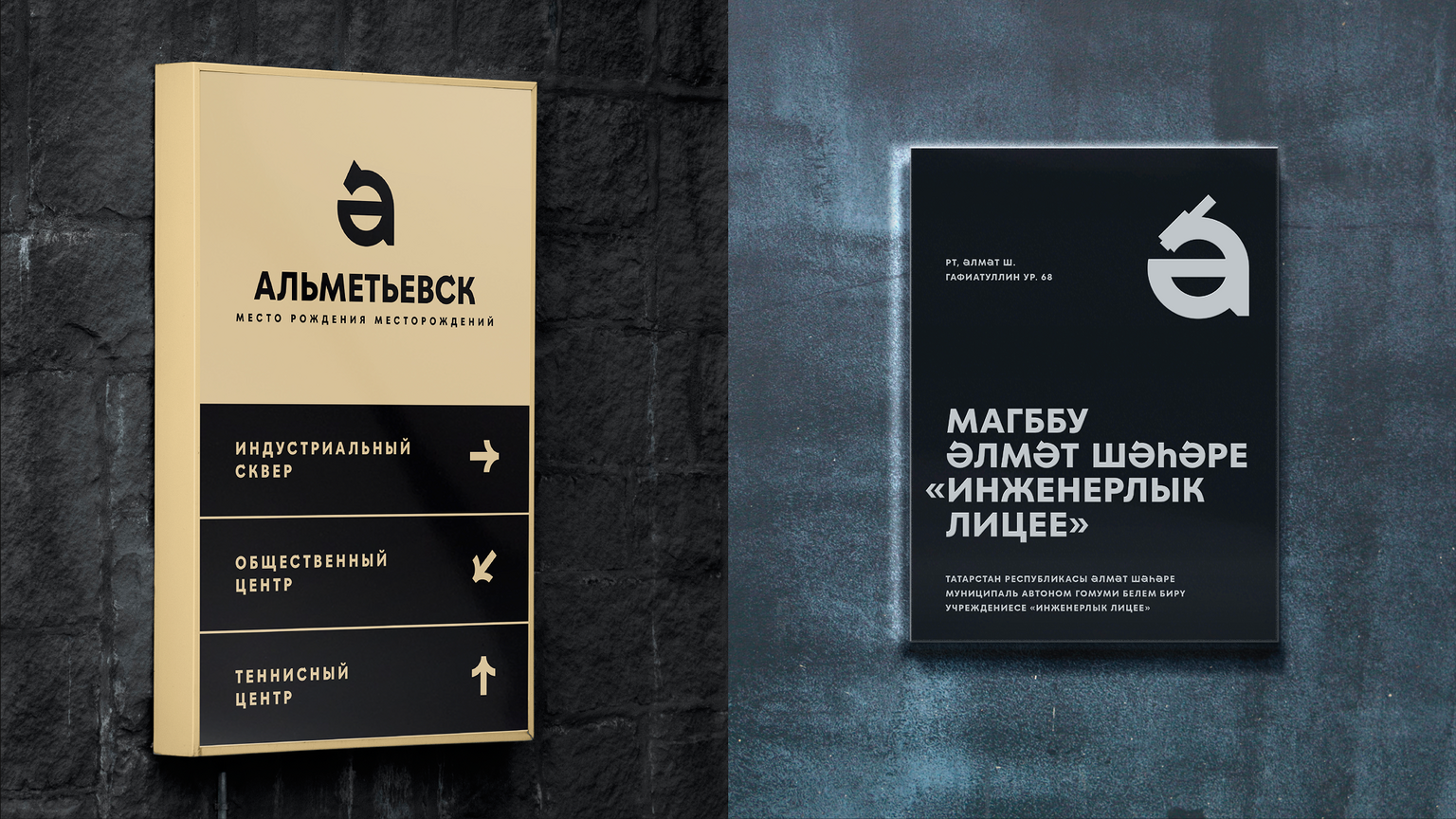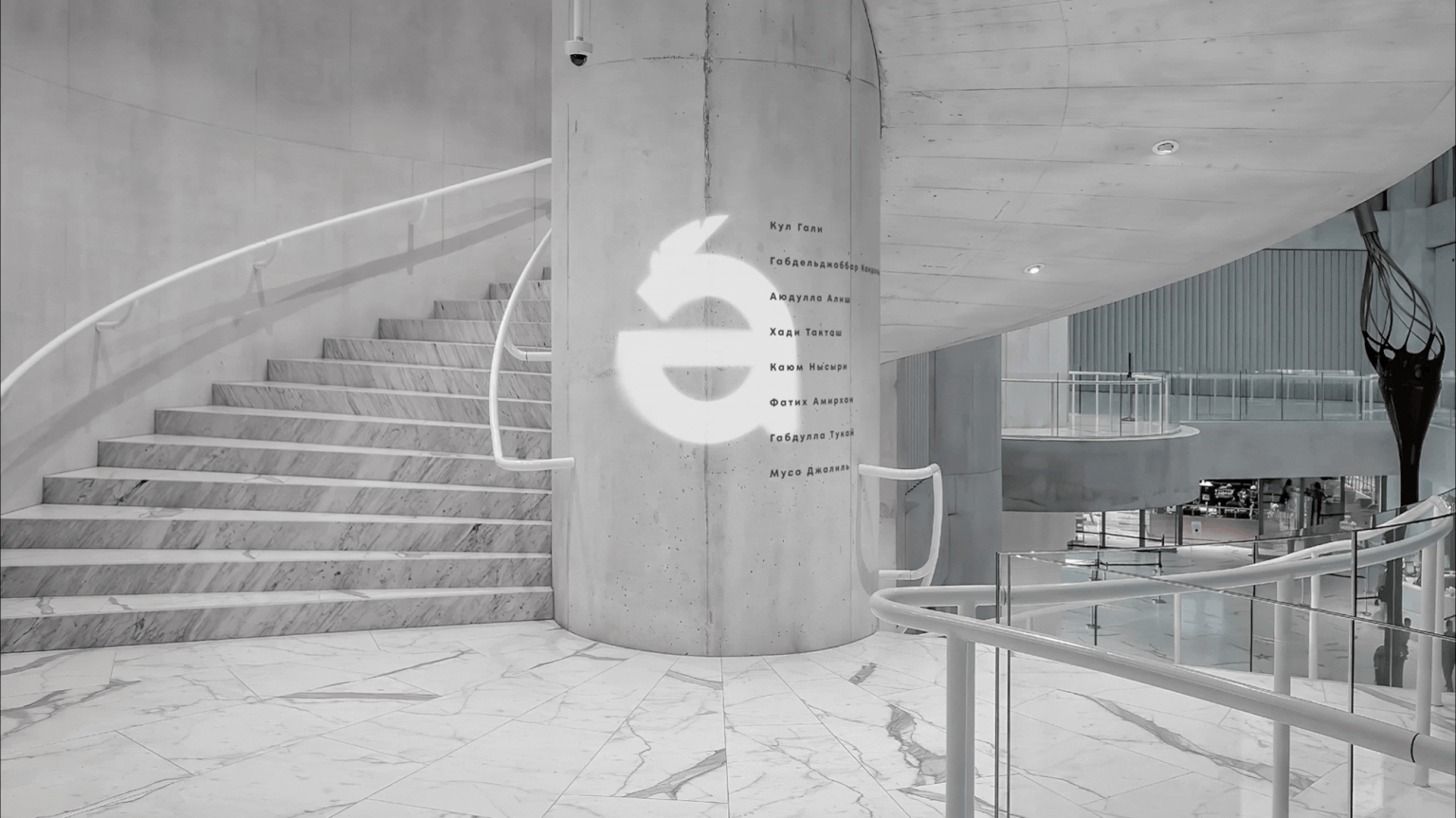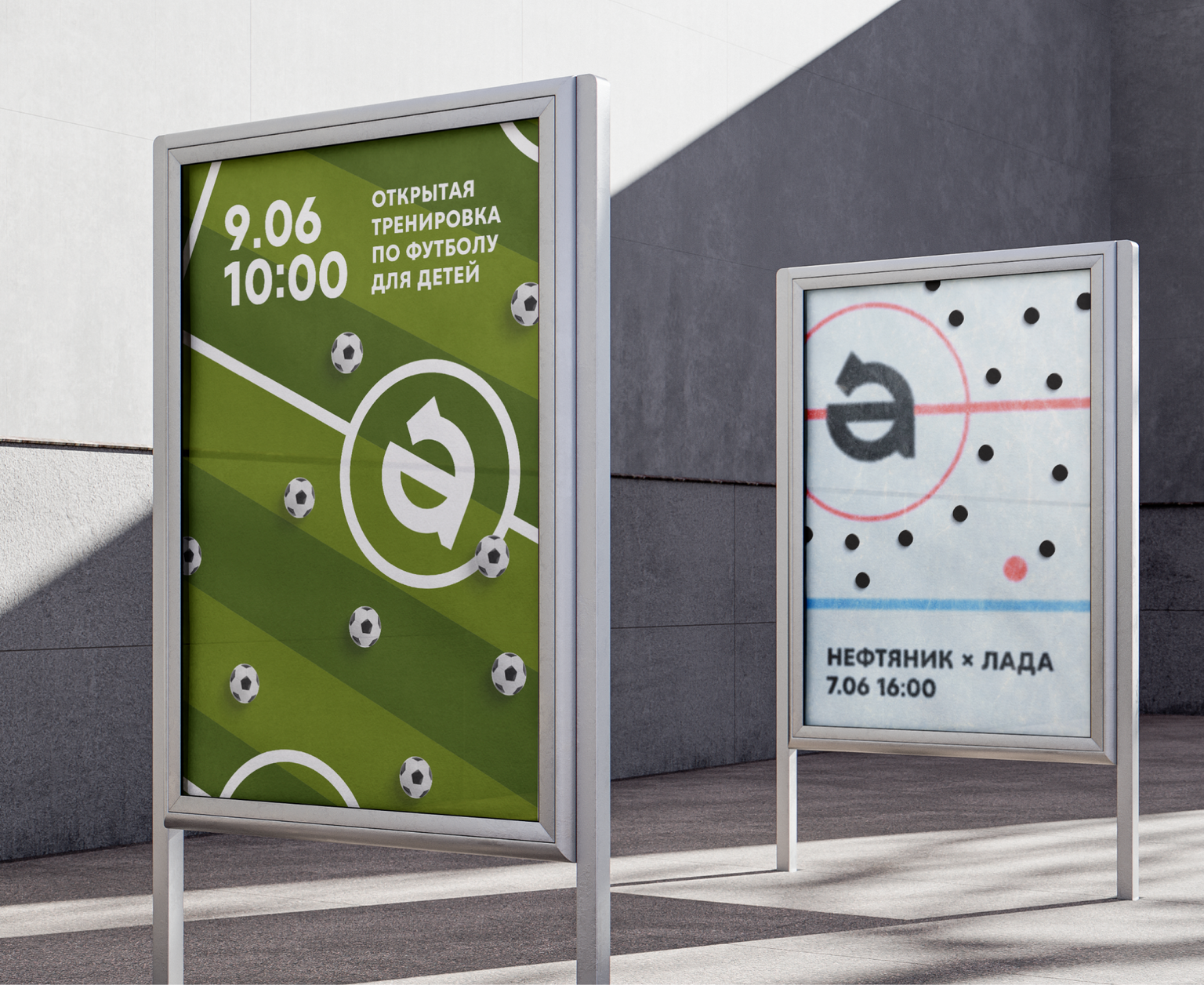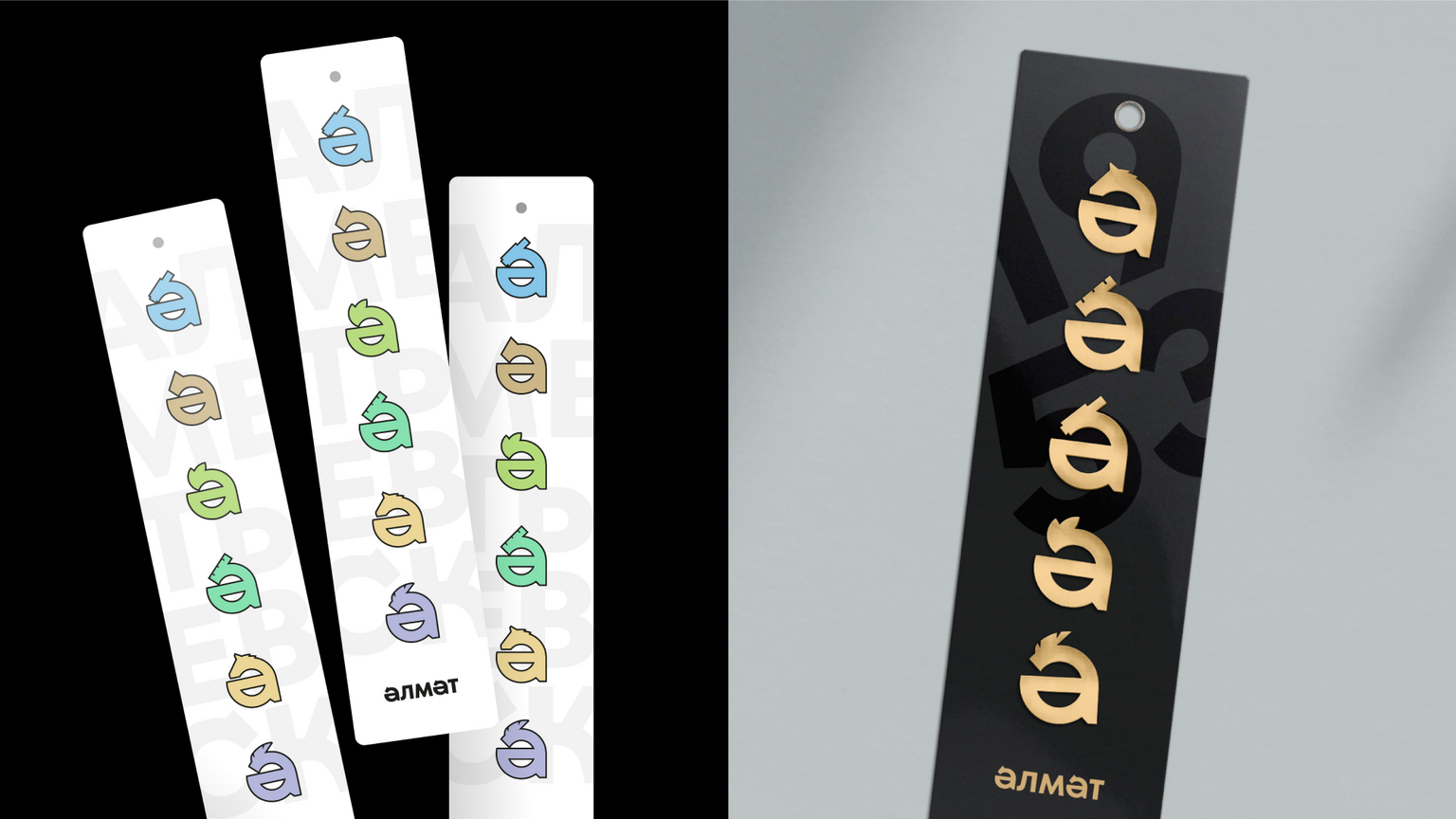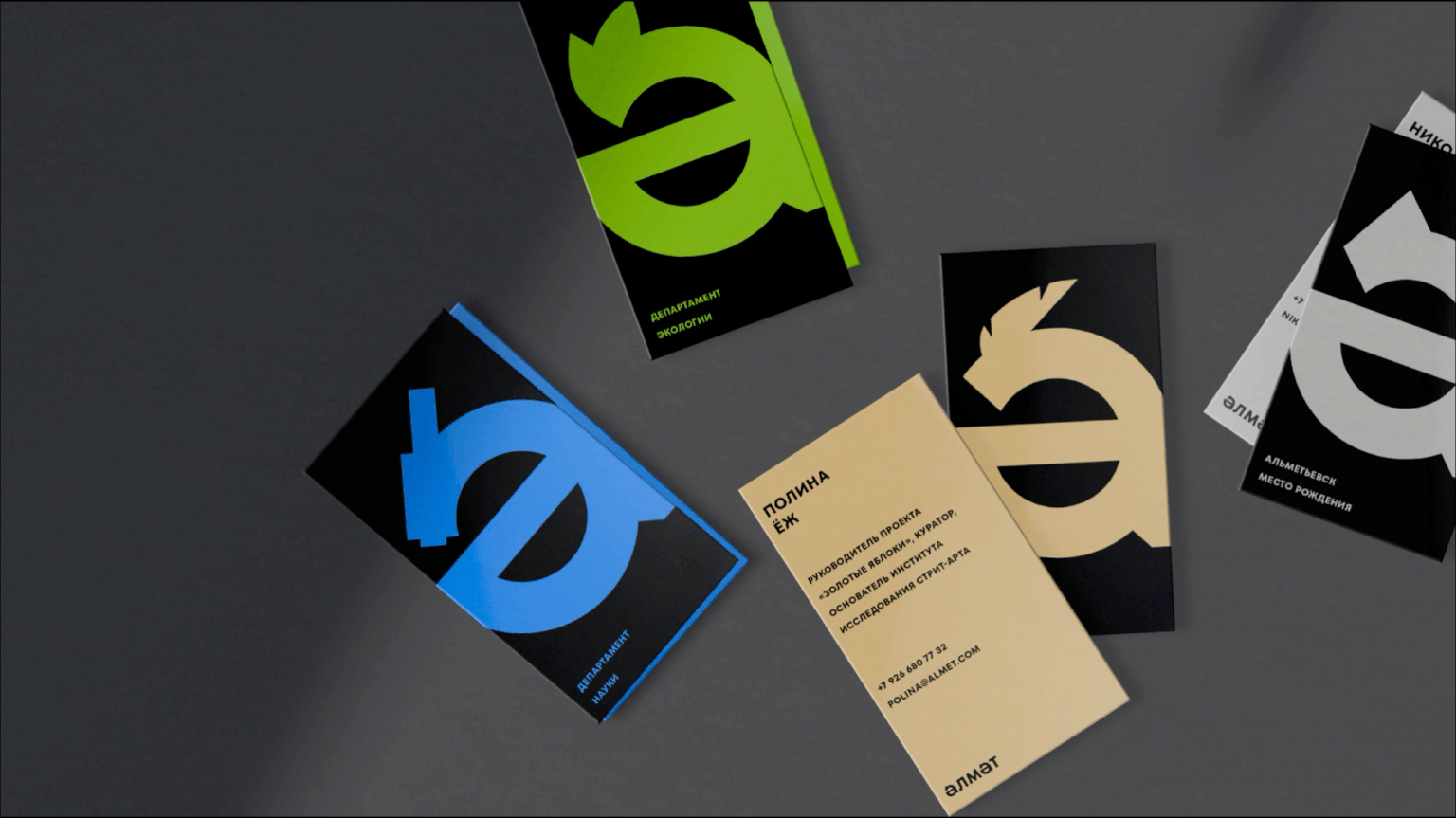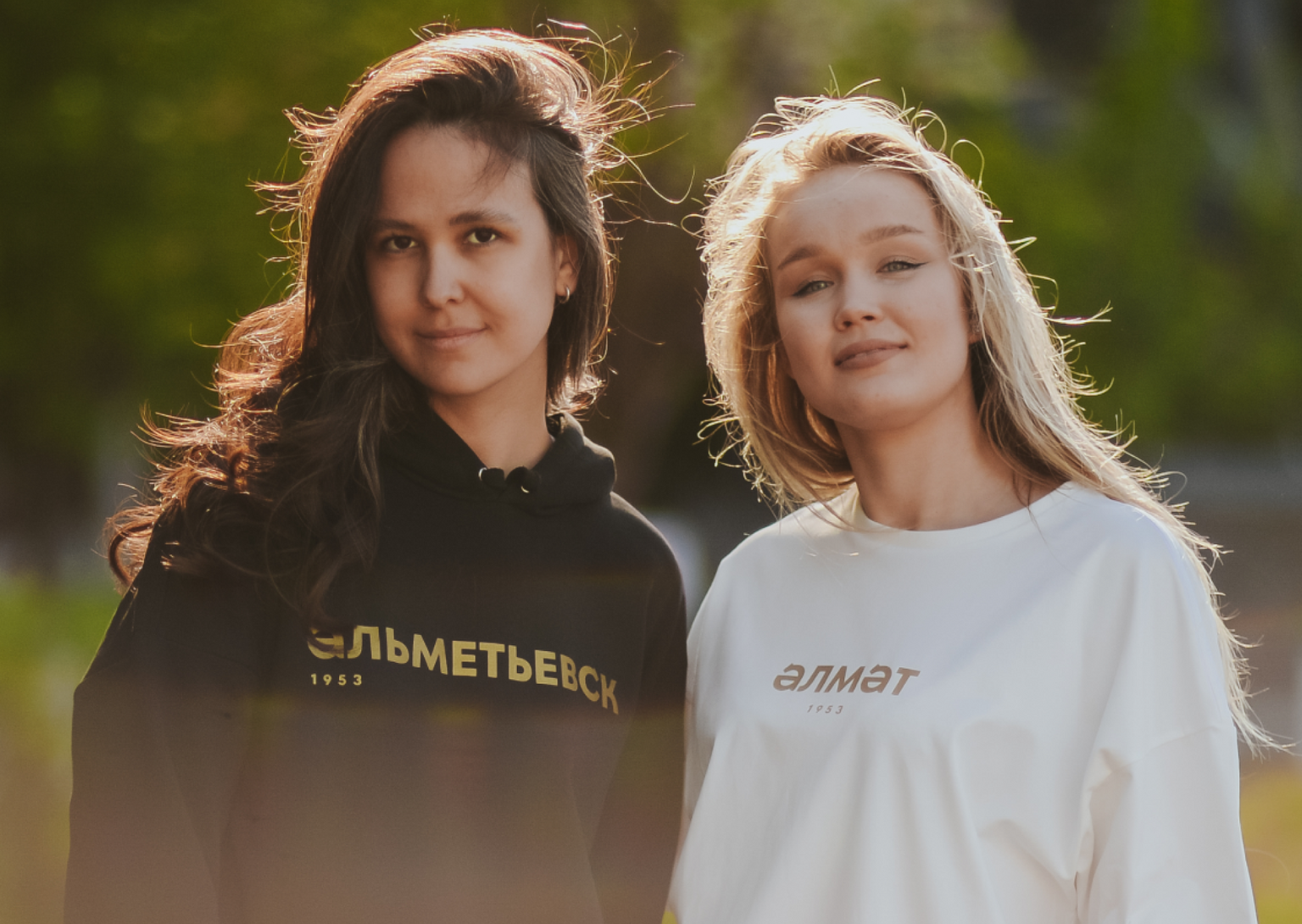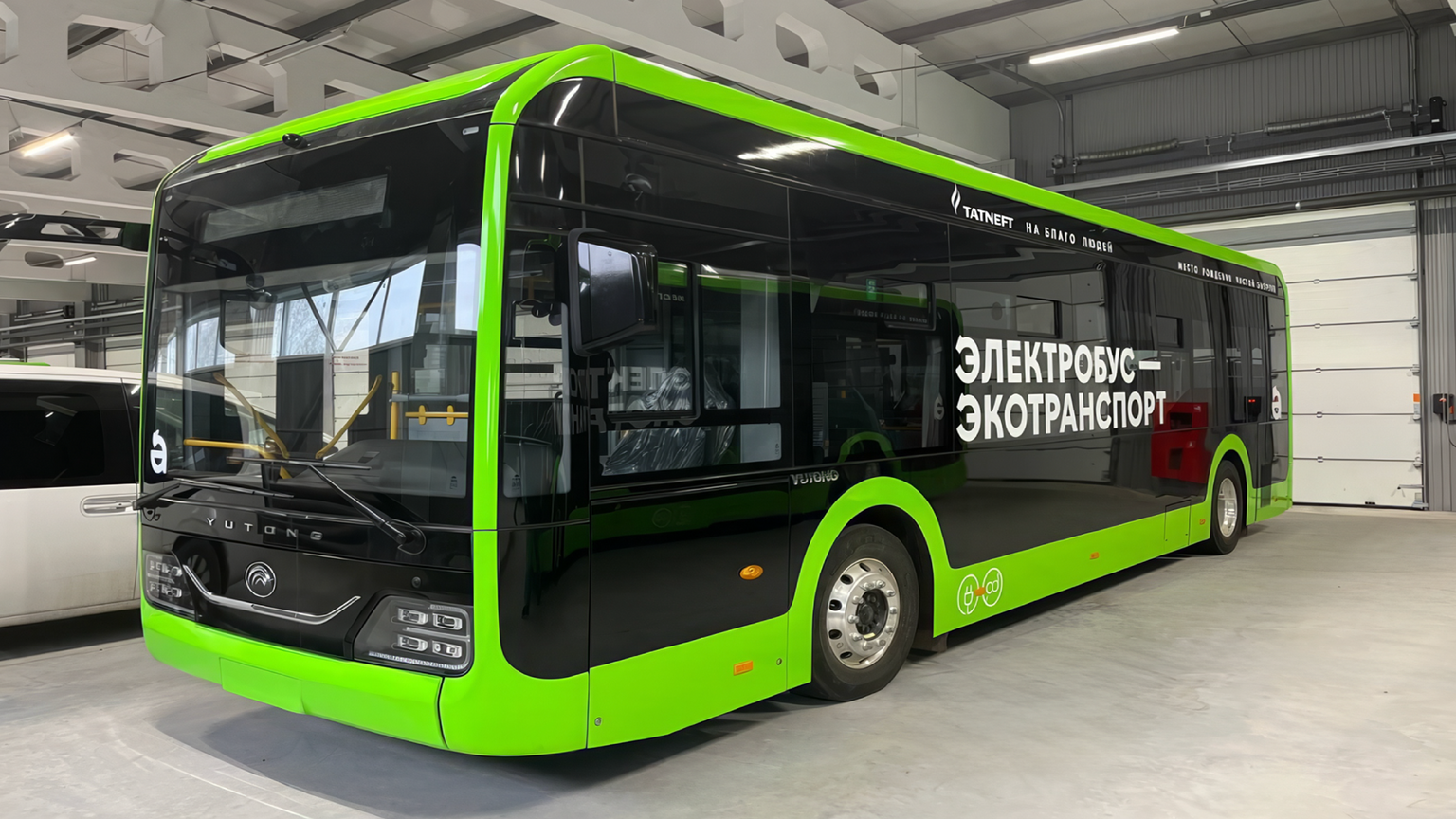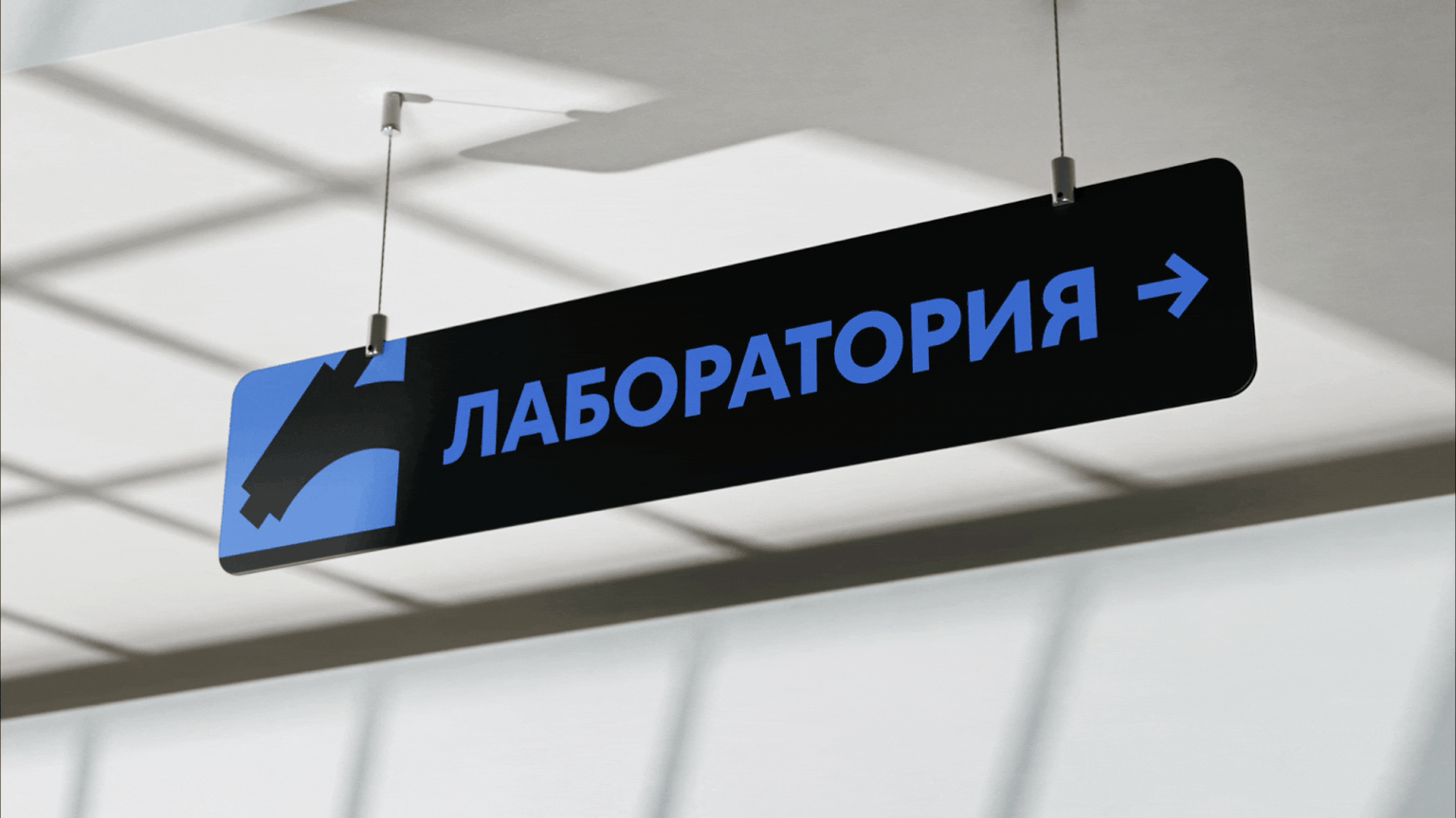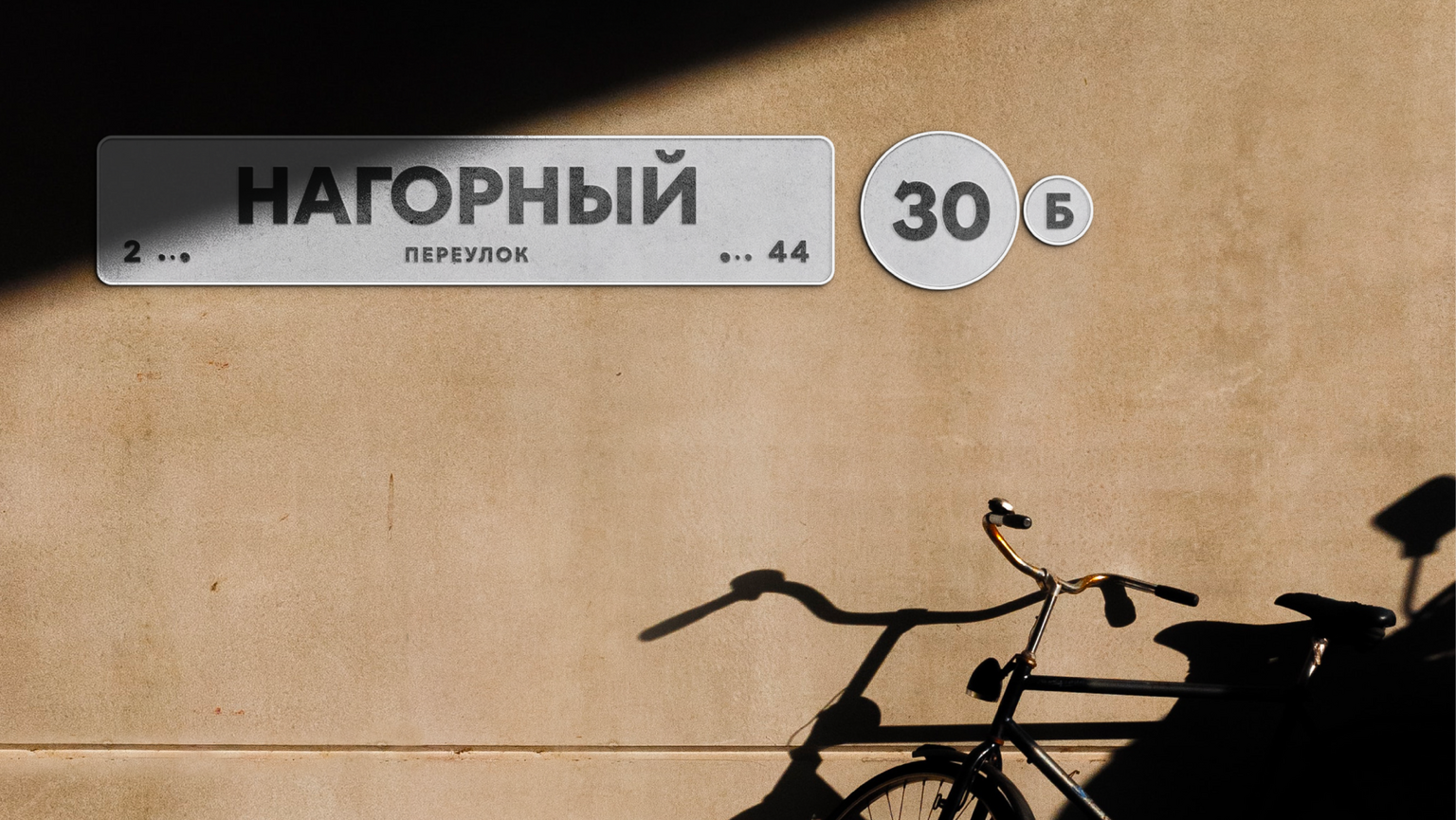
Модернизировали лаконичный TT Fors для территориального бренда Альметьевска: получившийся шрифт TT UVT Origin стал уникальным голосом города.
Альметьевск — город на юго-востоке Татарстана, один из важнейших центров российской нефтедобывающей промышленности. TT UVT Origin с оригинальными деталями и самобытной татарской пластикой визуально отразил смыслы, заложенные в новый бренд города. Шрифт уже активно используется в различных областях: от навигационных табличек и городских указателей до оформления телеканалов и официальных коммуникаций.